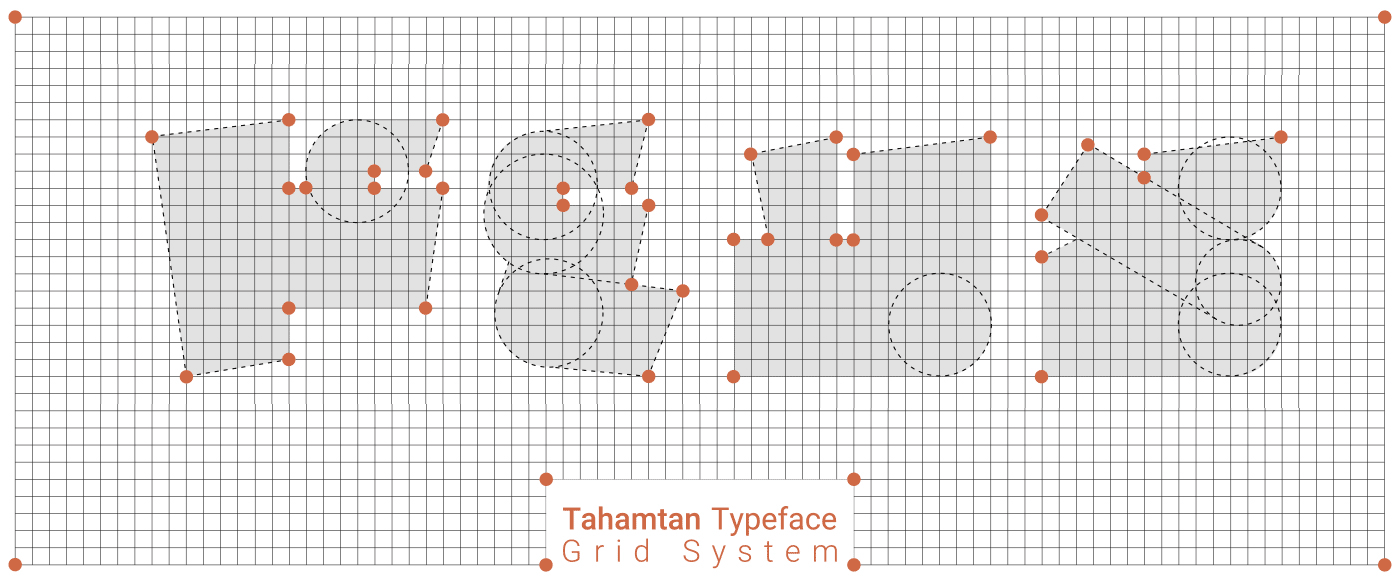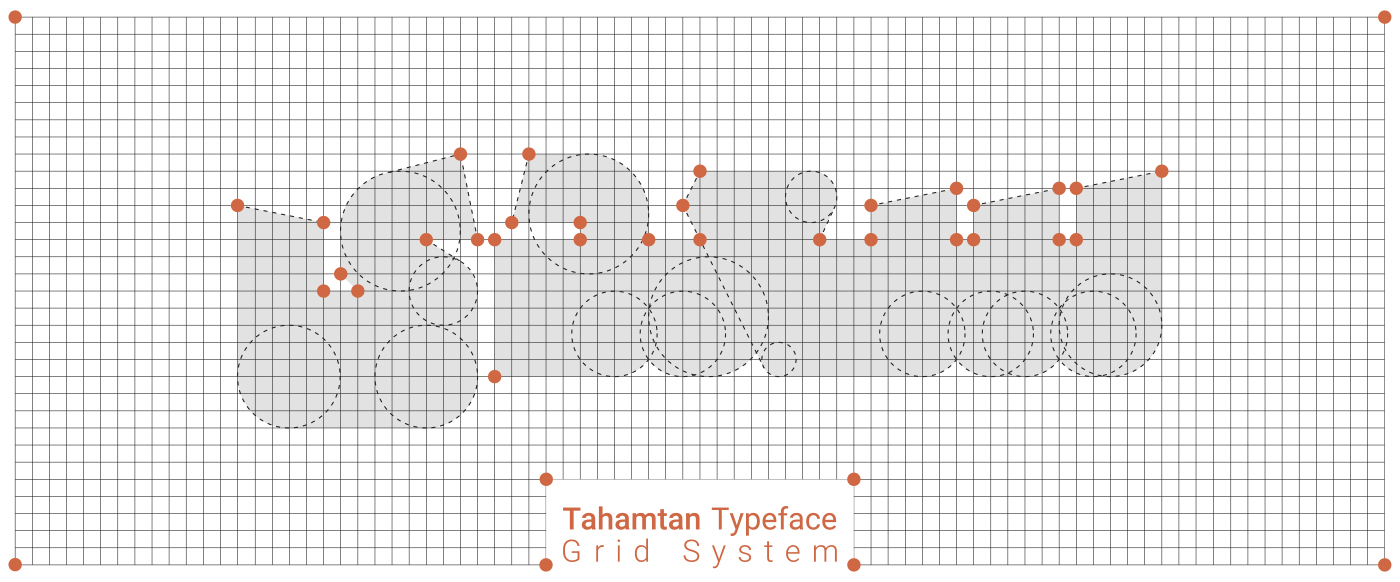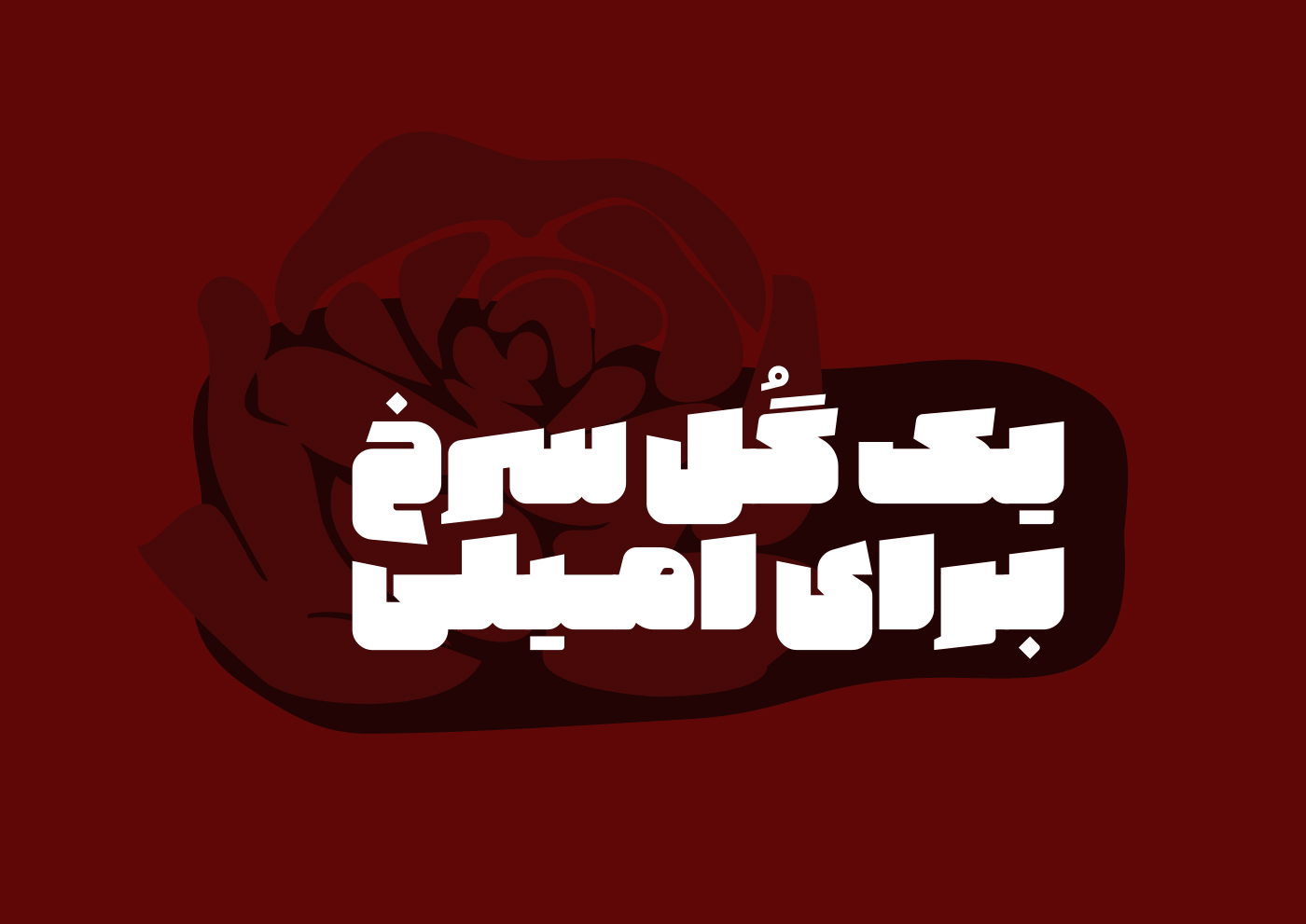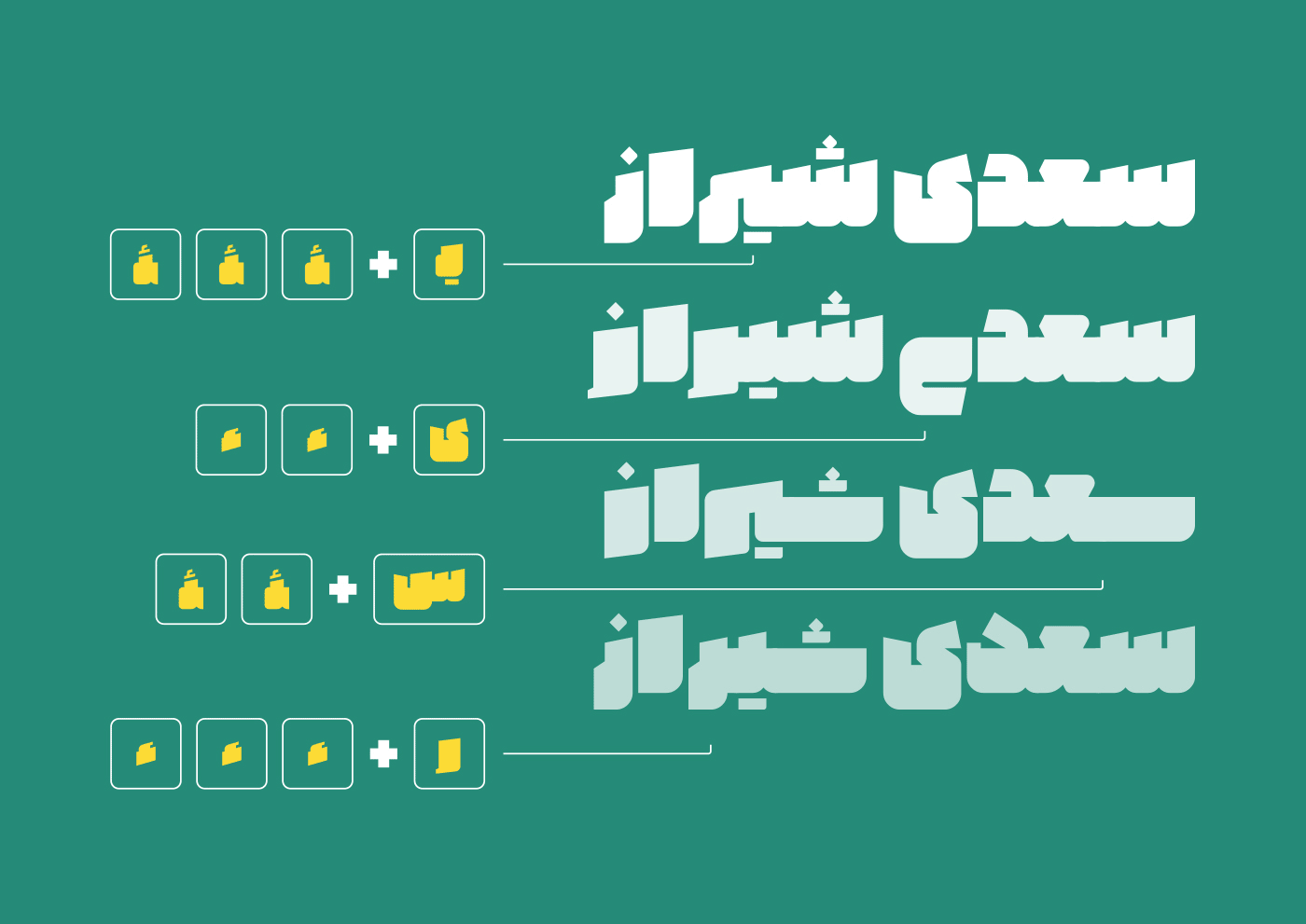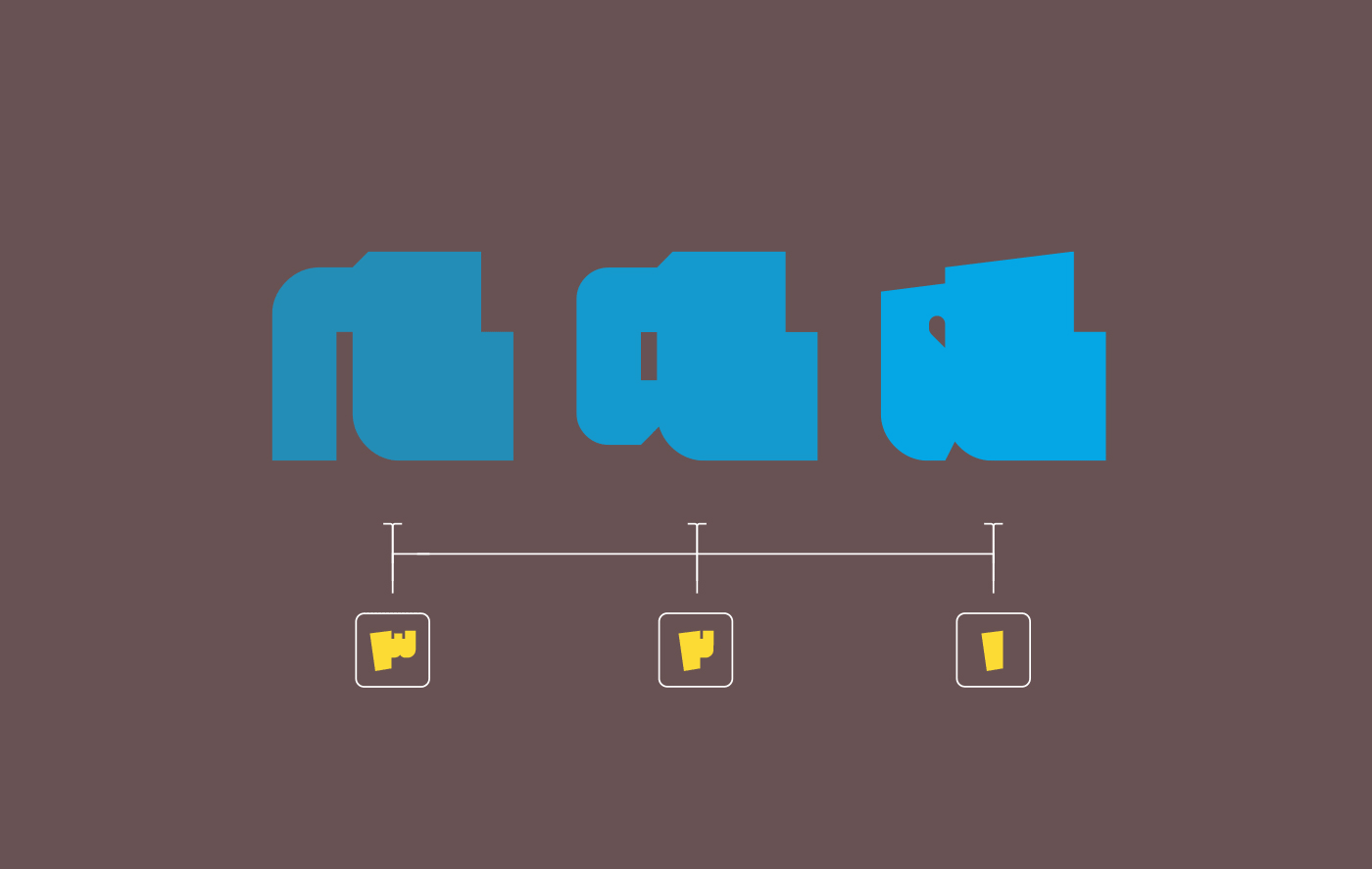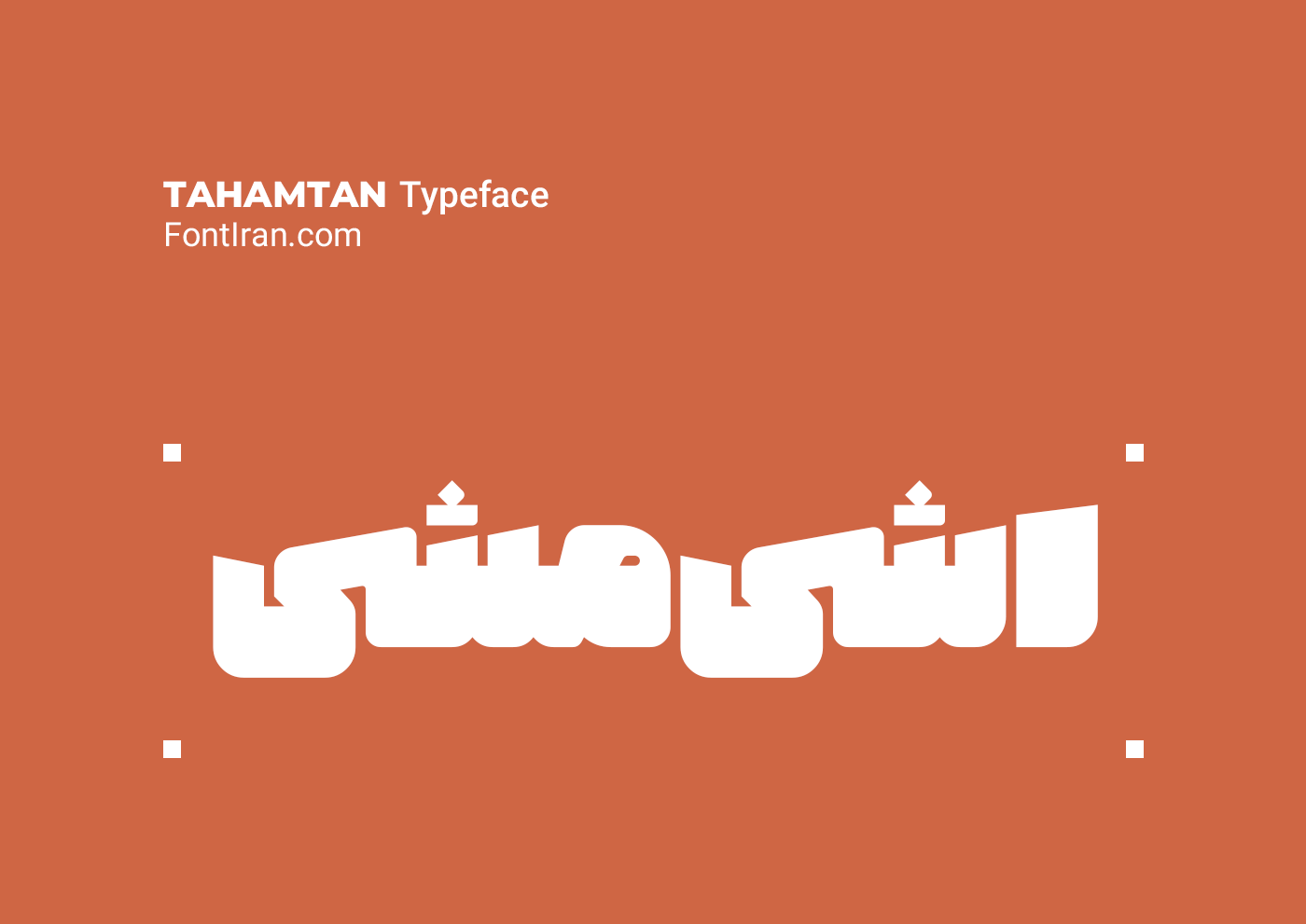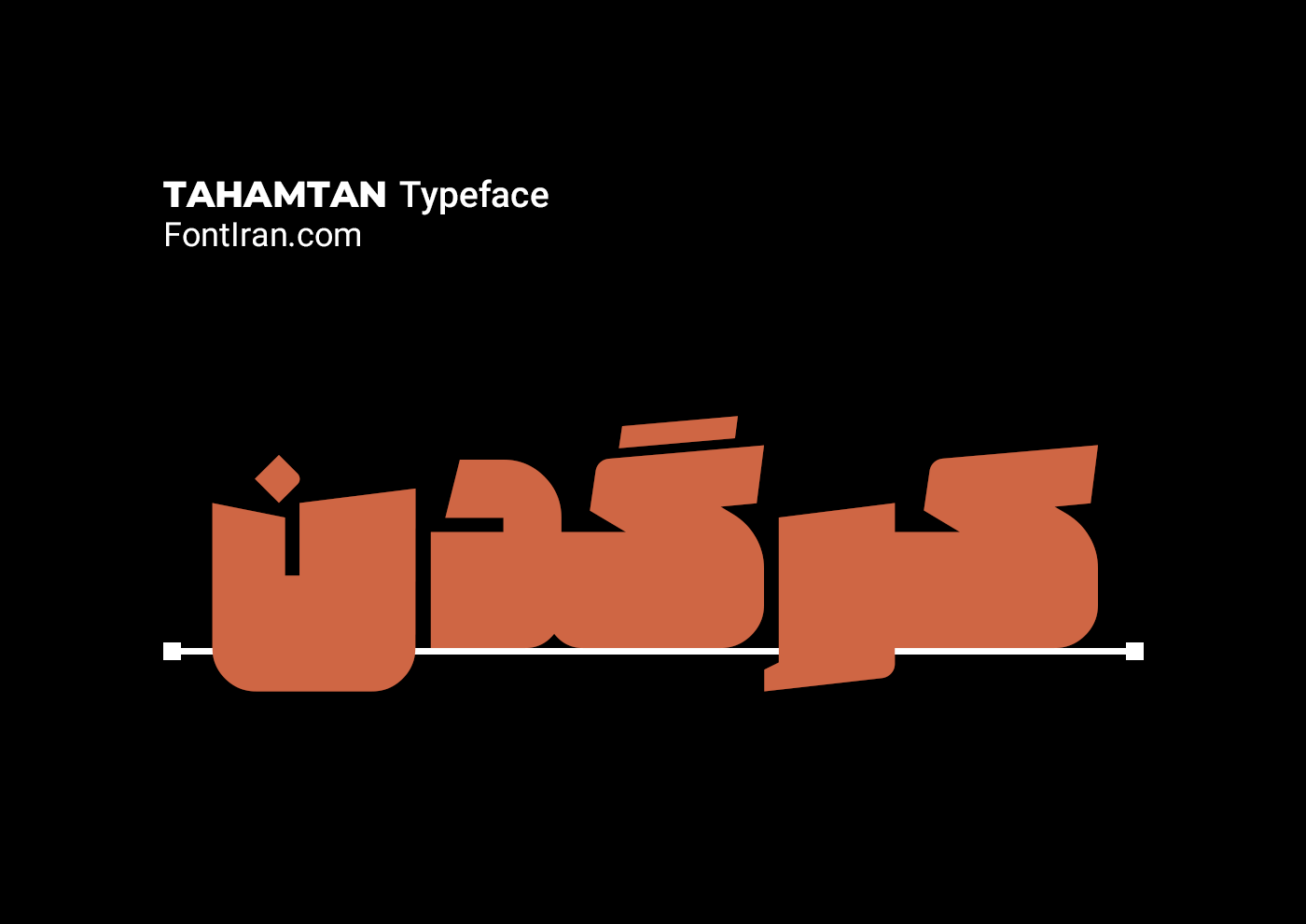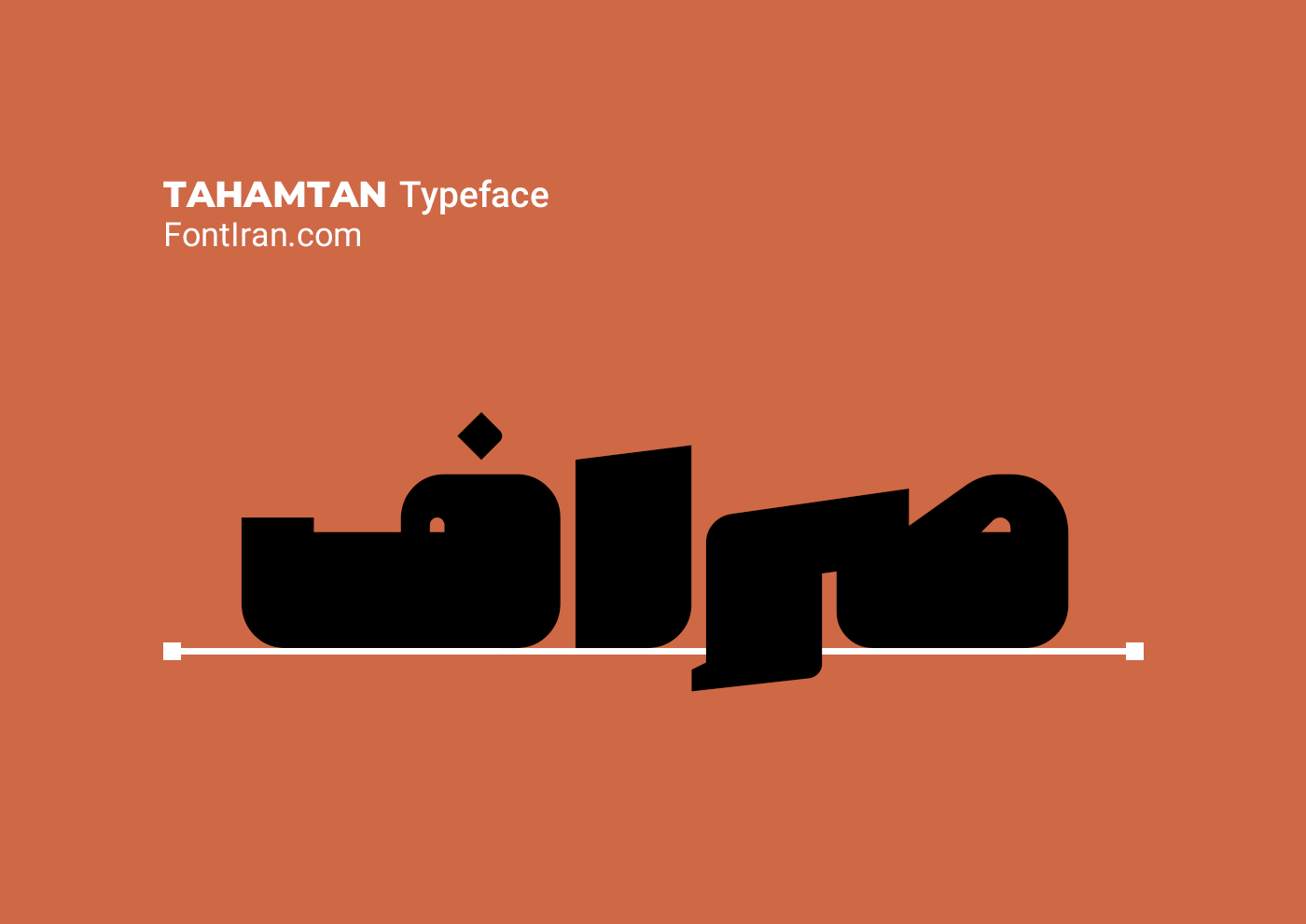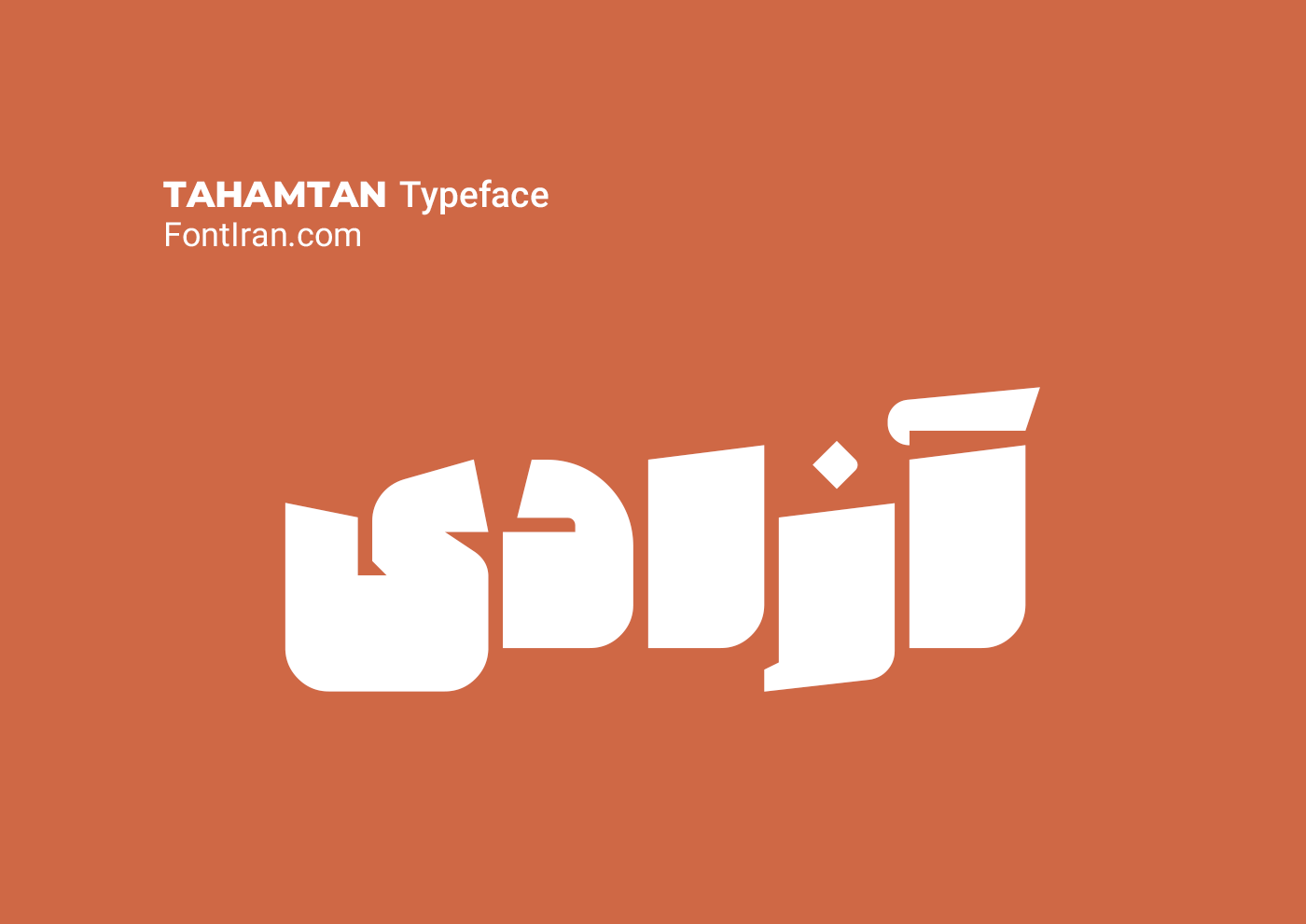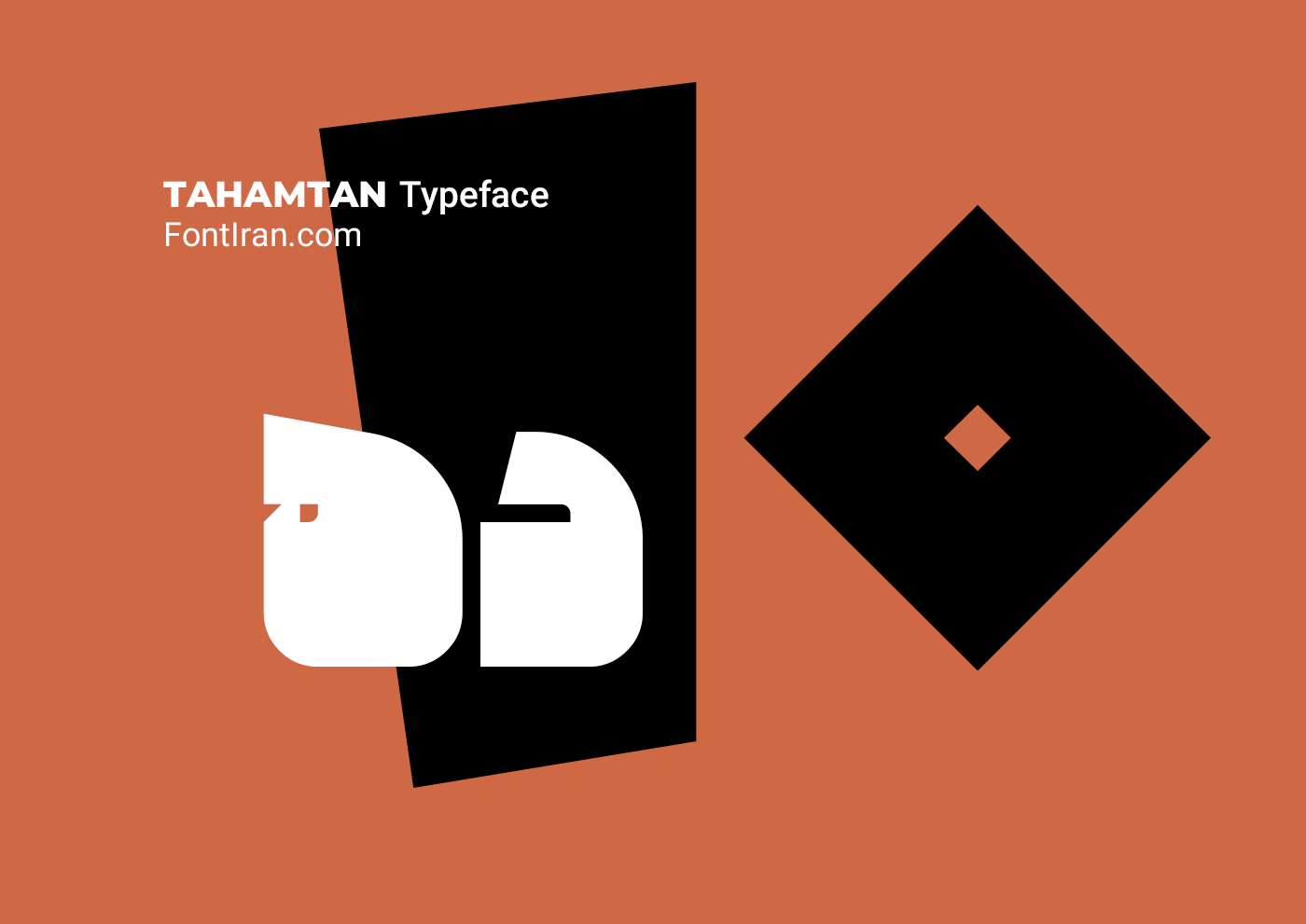
قلم تهمتن بر روی یک گرید سیستم (Grid System) ساخته شده و طراحی حروف آن با این ایده شکل گرفته است که فقط یک واحد به فضای منفی حروف اختصاص داده شود تا حروف با حداکثر سیاهی به دست آید.
این حجم از سیاهی و فضای مثبت باعث میشود نوشته بیشتر از هر فونتی خودنمایی کند و نادیده گرفتنش بسیار سخت باشد.
فونت تهمتن دارای ترکیبات و حروف جایگزین چندگانه است که میتوانید بصورت انتخابی از هریک از شکلهای حروف استفاده کنید.
در این قلم برای دستیابی به حرکت روان و راحت چشم در دنبال کردن کلمات در راستای افقی، حروف تا جای ممکن و بیشتر از حد معمول روی خط کرسی نشانده شدهاند.